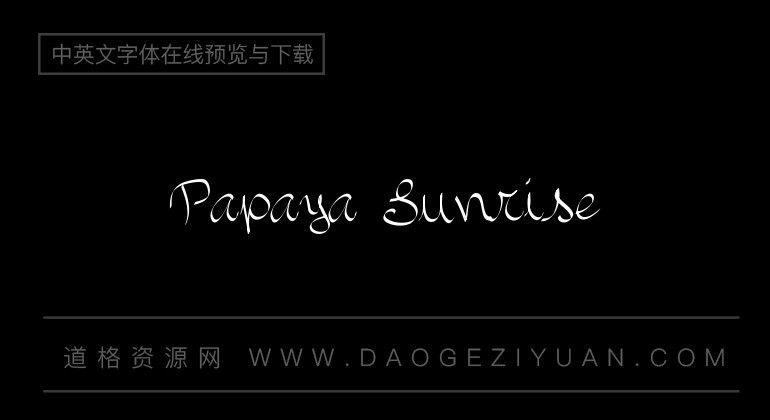
Papaya Sunrise是一种手写风格的字体,具有轻松、自然、流畅的感觉。它的字母形状略微倾斜,呈现出一种轻松自由的感觉,适合用于卡片、海报、包装、标志、品牌字体和其他设计项目中,可以为文本添加一些个性和趣味性。 Papaya Sunrise 的字母形态清晰,具有良好的可读性,并且包含有小写字母、大写字母、数字和标点符号。其字体文件支持多种文件格式,如TTF、OTF和WOFF,可以在各种设计软件中使用。 Papaya Sunrise适用于多种设计项目,如派对邀请函、婚礼卡片、海报、T恤设计、品牌标志等等。它的自然流畅性和个性化风格使其成为设计师们喜欢的字体之一。内容介绍
Papaya Sunrise是一款非常不错的手写艺术字体,具有很好的视觉感,适合于文化类的宣传设计、商业类品牌的广告和产品包装设计以及个性化文字排版等较多场景。